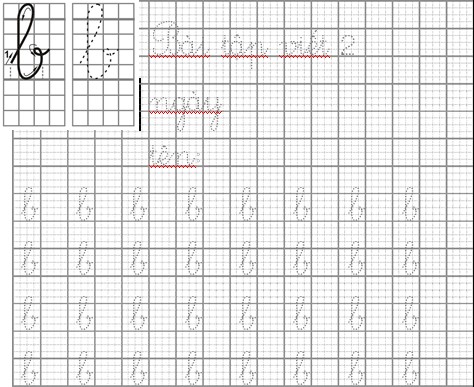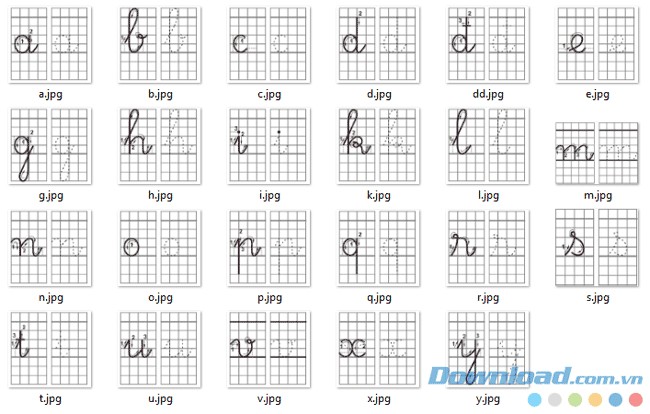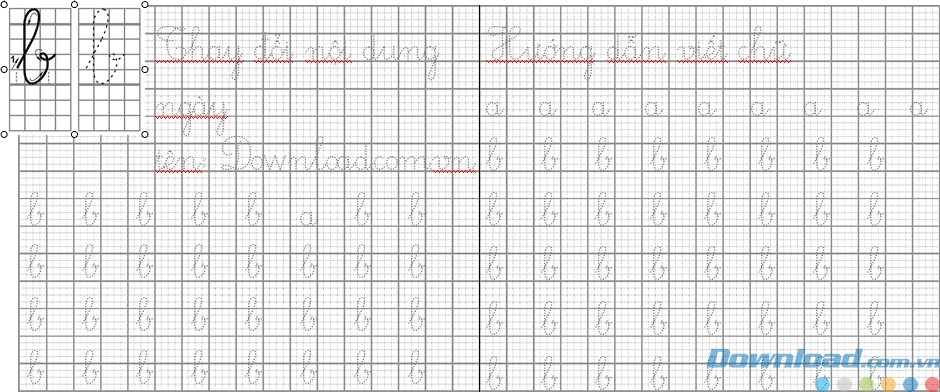
Font Unitapviet: Giải Pháp Tập Viết Tiếng Việt Hiện Đại Cho Học Sinh Tiểu Học
Font Unitapviet được thiết kế như một bộ phông chữ chuyên dụng, hỗ trợ đắc lực cho việc tập viết của học sinh tiểu học. Bộ phông này đặc biệt chú trọng đến việc tái hiện nét chữ mềm mại, tương đồng với phong cách luyện viết chuẩn mực của học sinh lớp 1.
Hầu hết mọi người đều đã từng làm quen với các cuốn vở tập tô chữ truyền thống khi mới bắt đầu bước vào lớp 1. Tuy nhiên, với bộ phông chữ này, bạn hoàn toàn có thể tự tạo ra các bài tập tô chữ theo ý muốn.
Bạn có thể tùy biến nội dung, từ những chữ cái đơn lẻ cho đến các cụm từ, câu văn, hoặc thậm chí là những đoạn văn ngắn, để in ấn và cung cấp cho con em mình những tài liệu học tập phù hợp.
Việc tự tạo ra các bài tập viết sẽ khơi gợi hứng thú học tập cho trẻ, đồng thời có thể giúp bạn tiết kiệm chi phí mua sách tập tô chữ, đặc biệt đối với những em học sinh có niềm đam mê học hỏi.
Như có thể quan sát trong hình ảnh minh họa, toàn bộ các chữ cái đều được thiết kế với các đường nét đứt, tạo điều kiện thuận lợi cho trẻ trong việc luyện tập tô chữ theo đúng kỹ thuật và hình dáng chuẩn mực do Bộ Giáo dục và Đào tạo quy định.
Khả năng ứng dụng của bộ font chữ UNITapviet
- Bộ font chữ này cho phép bạn thiết kế các bảng nhận biết chữ cái với kích thước lớn, hỗ trợ trẻ tập viết dễ dàng hơn.
- Việc in ấn lại các chữ viết chưa đẹp của trẻ trở nên đơn giản, giúp trẻ luyện tập thường xuyên và tiết kiệm chi phí.
- Bạn có thể tạo ra những bài tập viết cá nhân hóa, sử dụng tên của trẻ, tên người thân hoặc những chủ đề quen thuộc, gần gũi, khơi gợi hứng thú học tập cho trẻ tại nhà.
UNITapviet mang đến sự linh hoạt trong việc tạo ra các tài liệu học tập phù hợp với từng cá nhân.
Việc sử dụng font chữ này giúp quá trình dạy và học chữ cái trở nên hiệu quả và thú vị hơn.
Việc sử dụng font UNI Tapviet kết hợp với bộ ảnh hướng dẫn sẽ giúp trẻ làm quen với các nét chữ một cách trực quan và dễ dàng hơn.
Hãy khuyến khích trẻ luyện tập thường xuyên để đạt được kết quả tốt nhất.